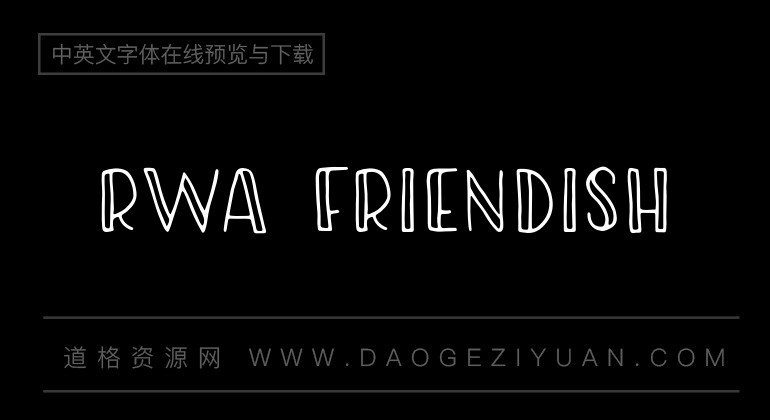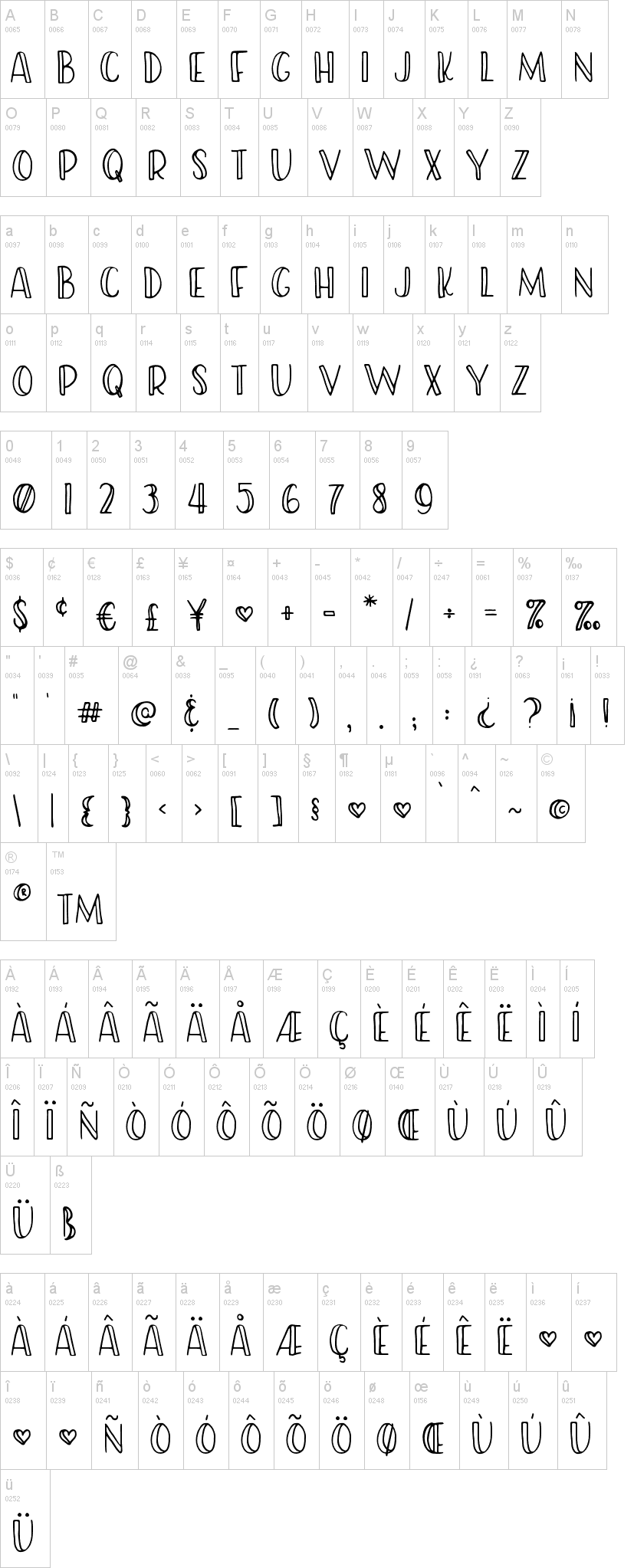
RWA Friendish是一款由RWA字体工作室设计的卡通字体,它具有活泼可爱的外观,适合用于传播正面讯息、活动宣传等场合。RWA Friendish字体采用多种细节处理,使字体更加生动有趣,具有明显的立体感,可以使文字更加生动有趣。内容介绍
RWA Friendish是一款非常不错的手写艺术字体,具有很好的视觉感,适合于文化类的宣传设计、商业类品牌的广告和产品包装设计以及个性化文字排版等较多场景。